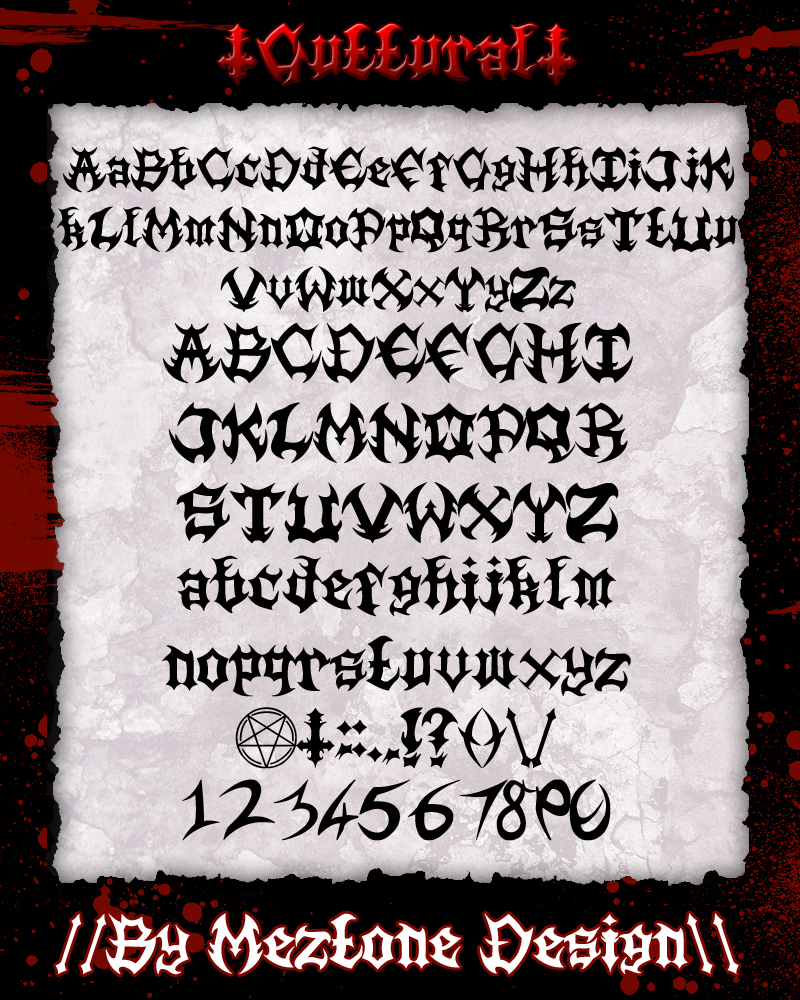
Guttural od studia Meztone Design je bezplatné gotické písmo s drsným středověkým nádechem. Písmena sází na těžké, tesané tvary a zahnuté, čepelovité hroty, což dodává verzálkám syrový, heraldický rytmus. Ten připomíná spíše staré nápisy a rukopisné nadpisy než uhlazené moderní gotické obměny.
Písmo se hodí na plakáty, metalové či punkové letáky, obaly alb, loga her nebo branding barů a tetovacích studií, kde dokáže bezplatný font s takovou ostrostí udávat tón celého vizuálu. Použijte jej na krátké titulky, úvodní karty nebo iniciály ve stylu monogramů, pokud hledáte husté, do sebe zapadající písmo, které působí, jako by bylo vykováno ze železa a ne kresleno perem.